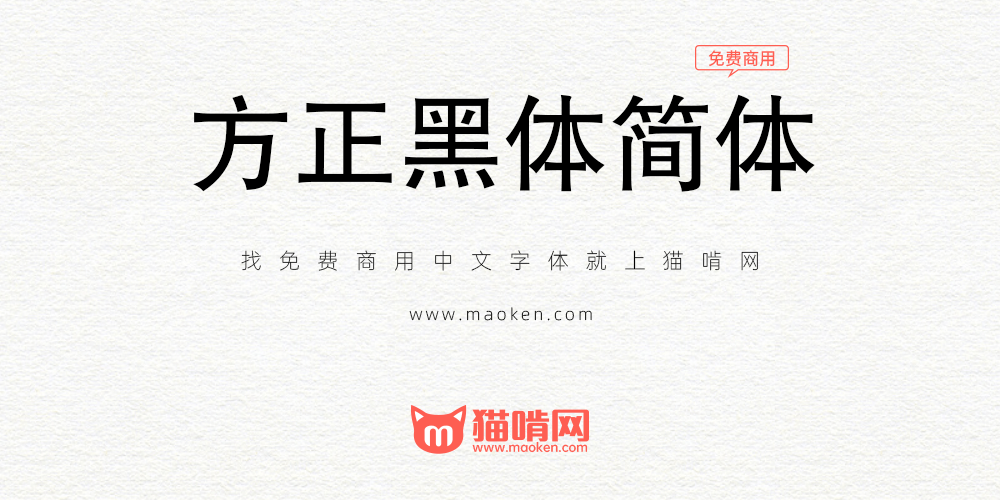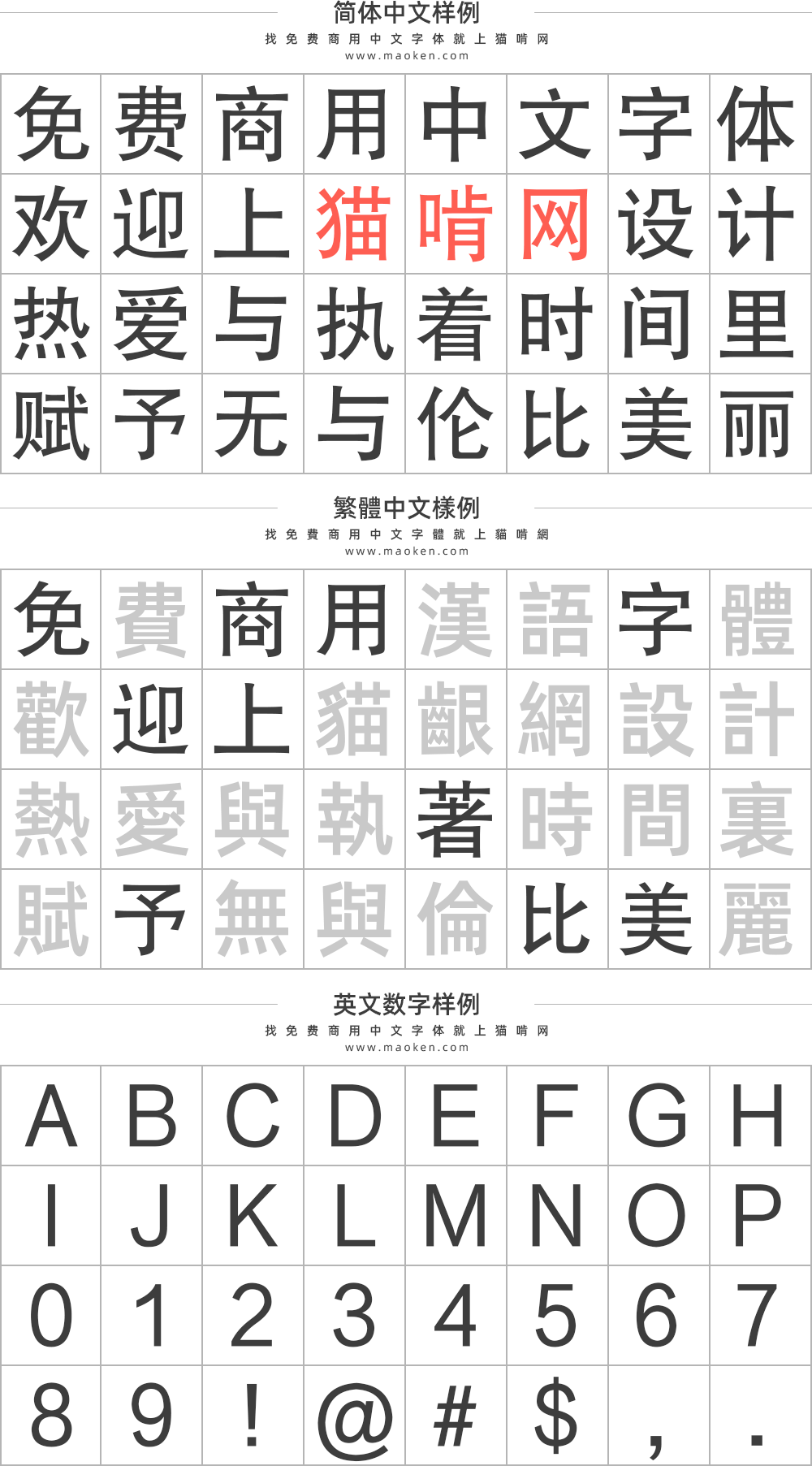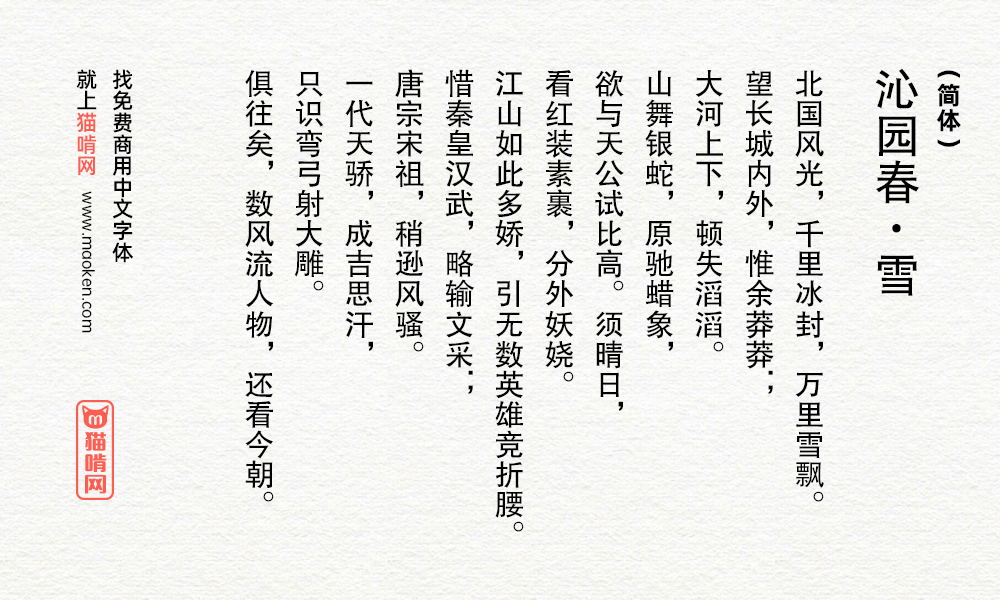
方正黑体简体:就是这么朴实无华的黑体字型免费商用
字体作者:方正 (中国大陆) 字体字重:1个
字体特色
「方正黑体」的设计源于铅字时代的黑体字稿,是一款专门为正文排版设计的黑体。方正黑体的笔画两端留有喇叭口,撇、捺、钩笔画的粗细变化较大,中宫比较紧凑。其字重适中、字形风格中性朴实,不但适用于印刷媒介,还可用于屏幕阅读,是一款非常经典的正文黑体。
方正黑体_GB18030 的西文部分很像 Helvetica,跟简体版的西文部分不同。
猫啃网6年前 (2020-06-26)回复